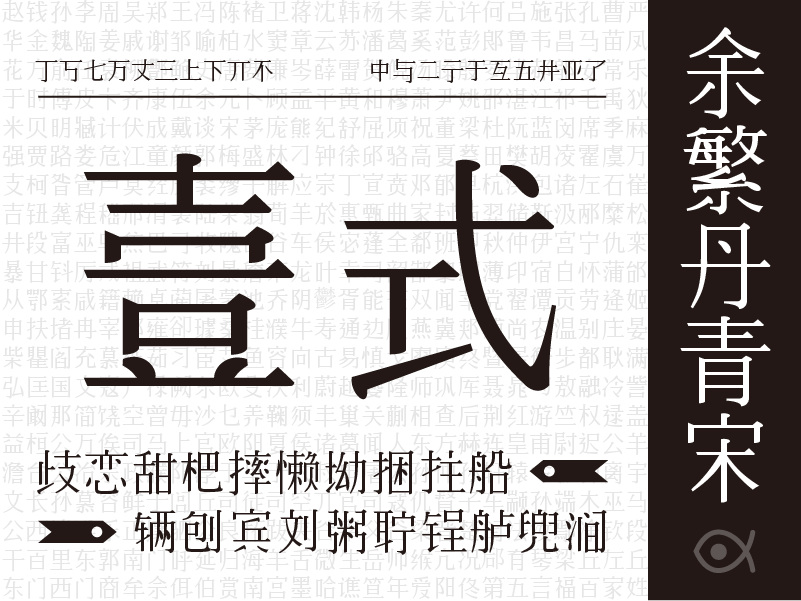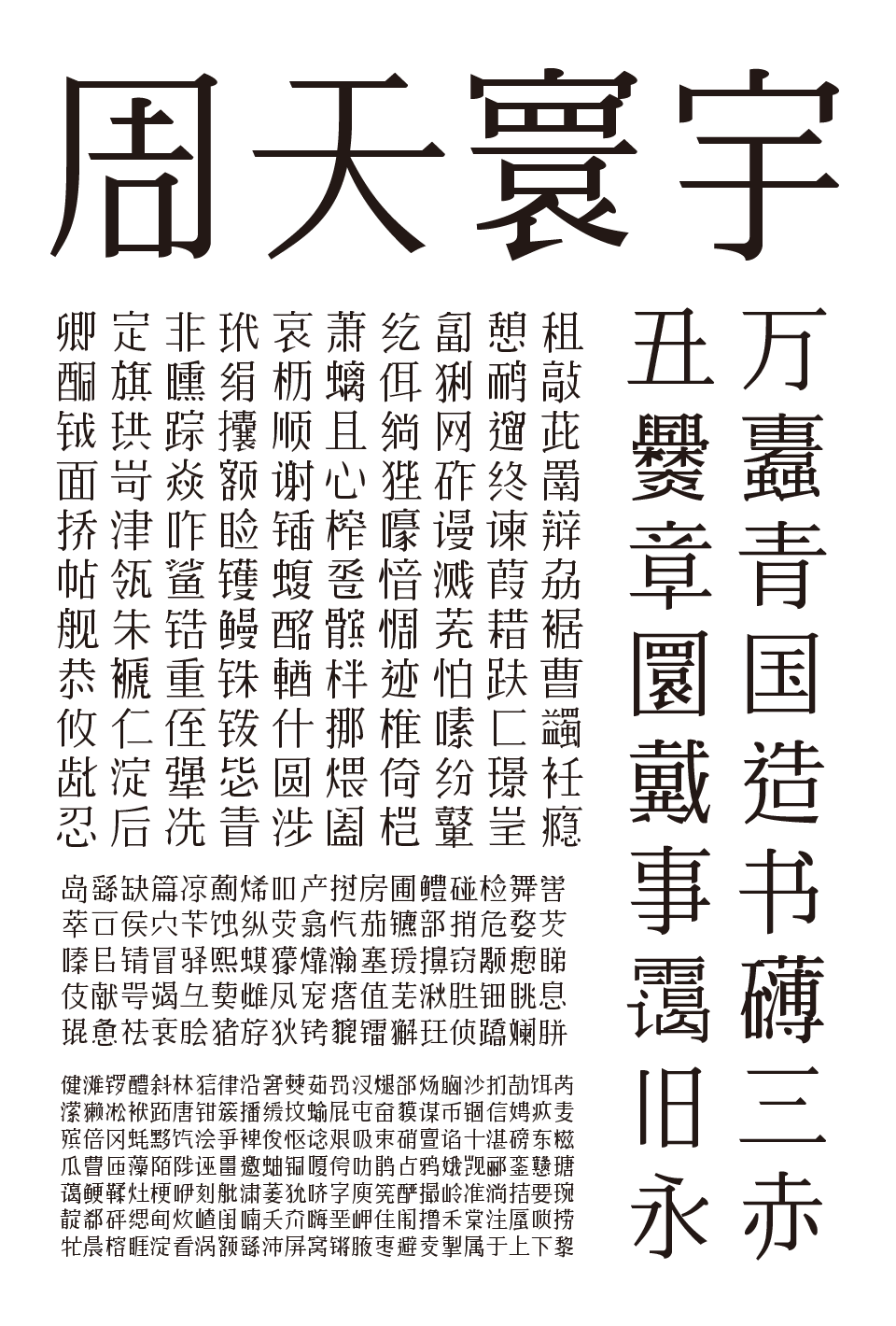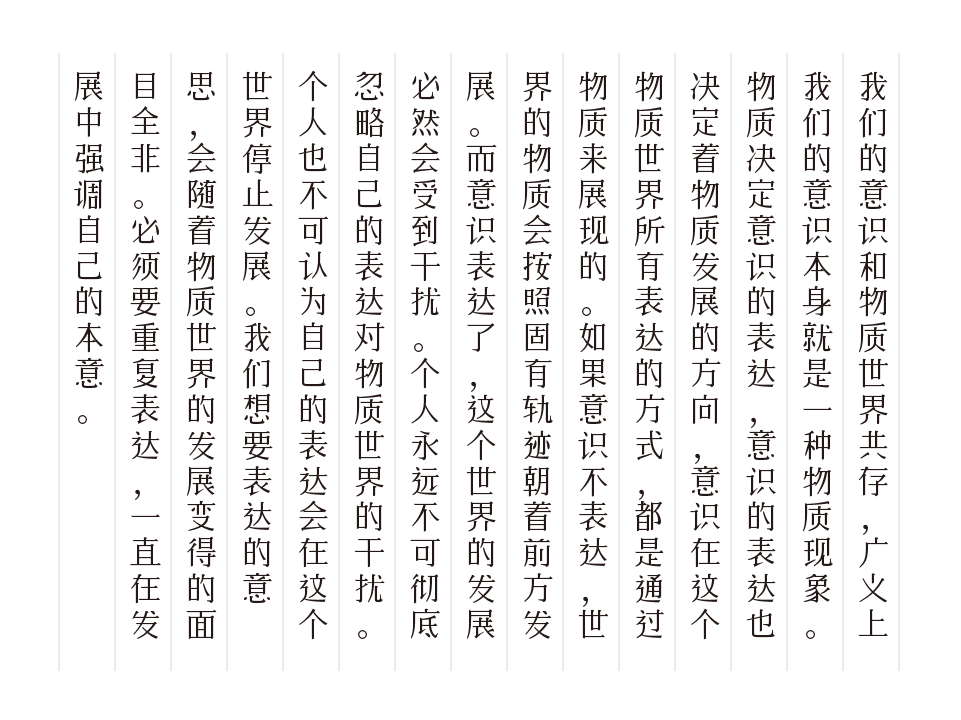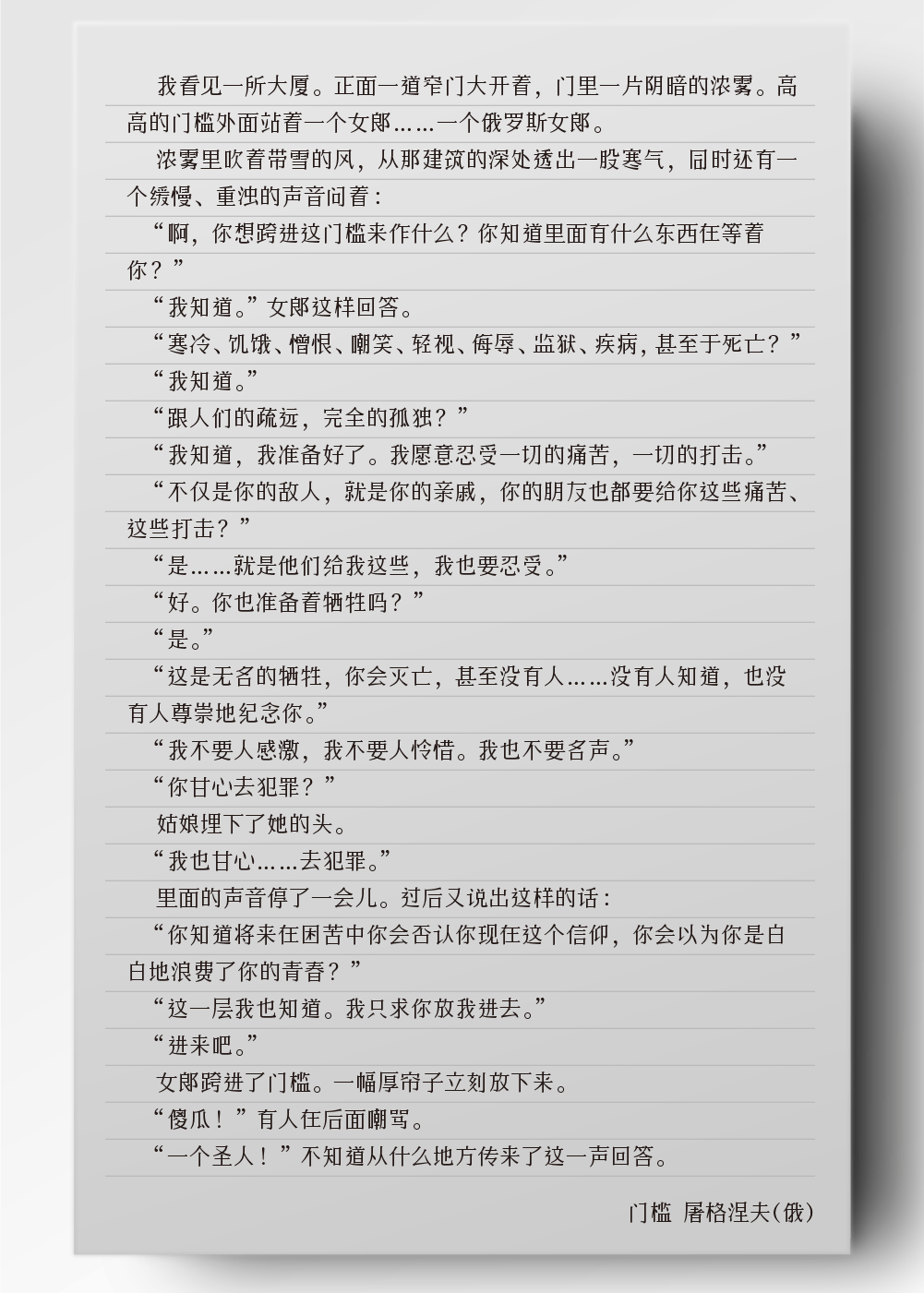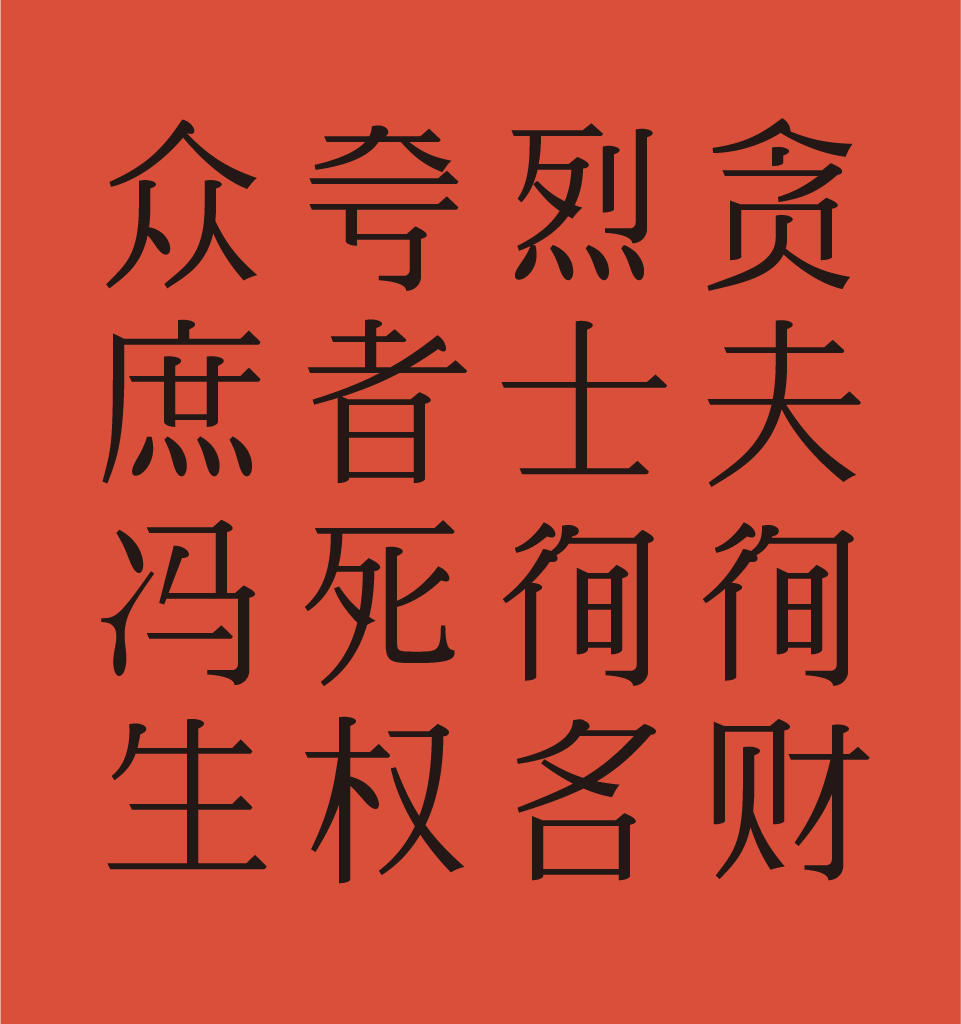
这套汉字的骨架结构全部来自动态组字系统繁星。当初动手写这部分代码,主要就是想顺着纯代码自动排布字形的一条线完整走通一遍,顺便测试下目前的算法逻辑在应对复杂汉字构造时,到底能稳定产出到什么程度。因为本质上还是个带点探索性质的实验项目,所以碰到部分部件拼合时显得有点卡顿,或是某些笔画长短粗细明显不太匹配的情况,我就不打算再去逐字手动微调了,直接把算法第一次跑出来的原始数据保留了下来。平心而论,现在拿到的这版字形确实还带着点机器生成的生硬感,在起收笔的弧度、重心平衡这些细腻的处理上,跟人工一笔一画反复推敲的字稿肯定没法放在一个天平上比较,它更像是一个处于持续优化阶段的早期雏形。整个工程文件已经全部整理好并上传到GitHub,如果你有相关的依赖环境,随时可以把仓库克隆下来,自己在本地跑几遍看看生成效果。另外,版面中配套的英文字母、数字和各类标点符号,为了保证视觉节奏不跳脱,我统一调用了思源宋体里的对应字形来补齐。整套字体遵循的是OFL-1.1开源协议,商用授权范围很宽泛,个人测试或者是放到正式的商业项目里都没有任何障碍,大家可以直接放心下载使用。